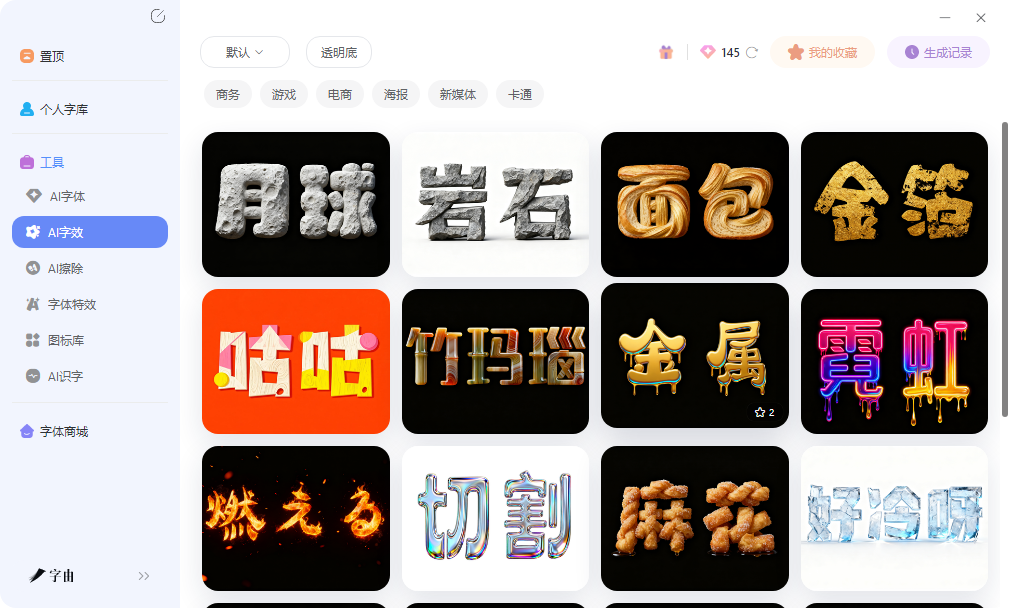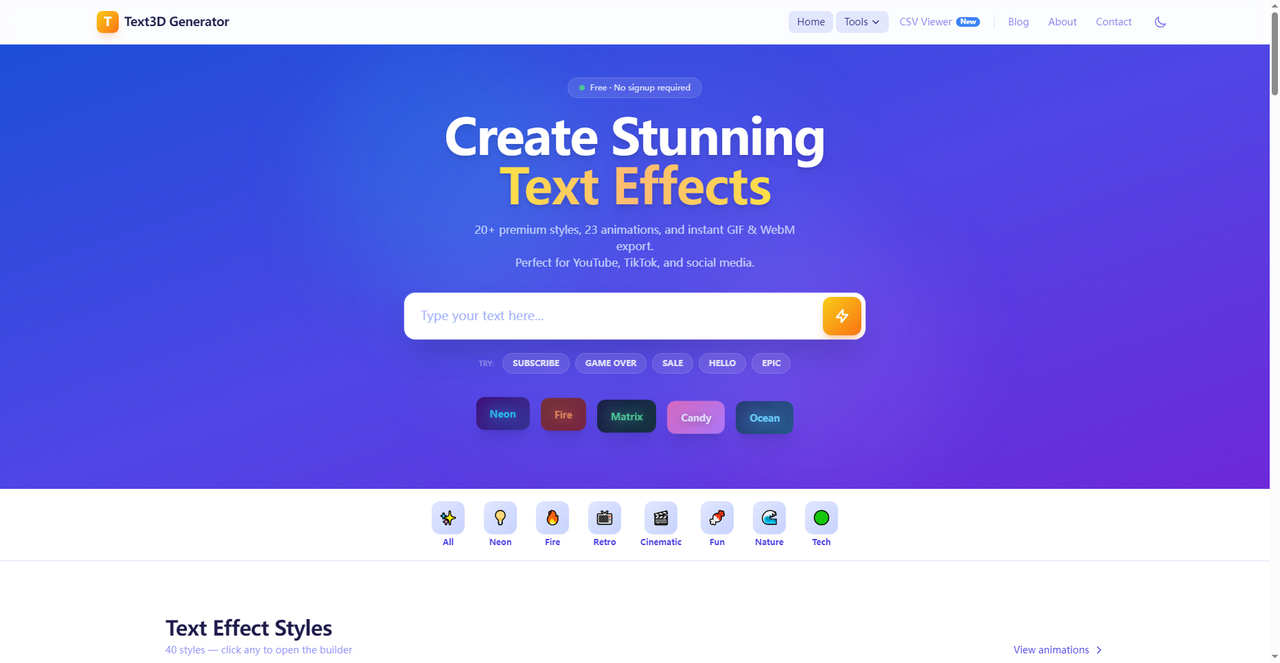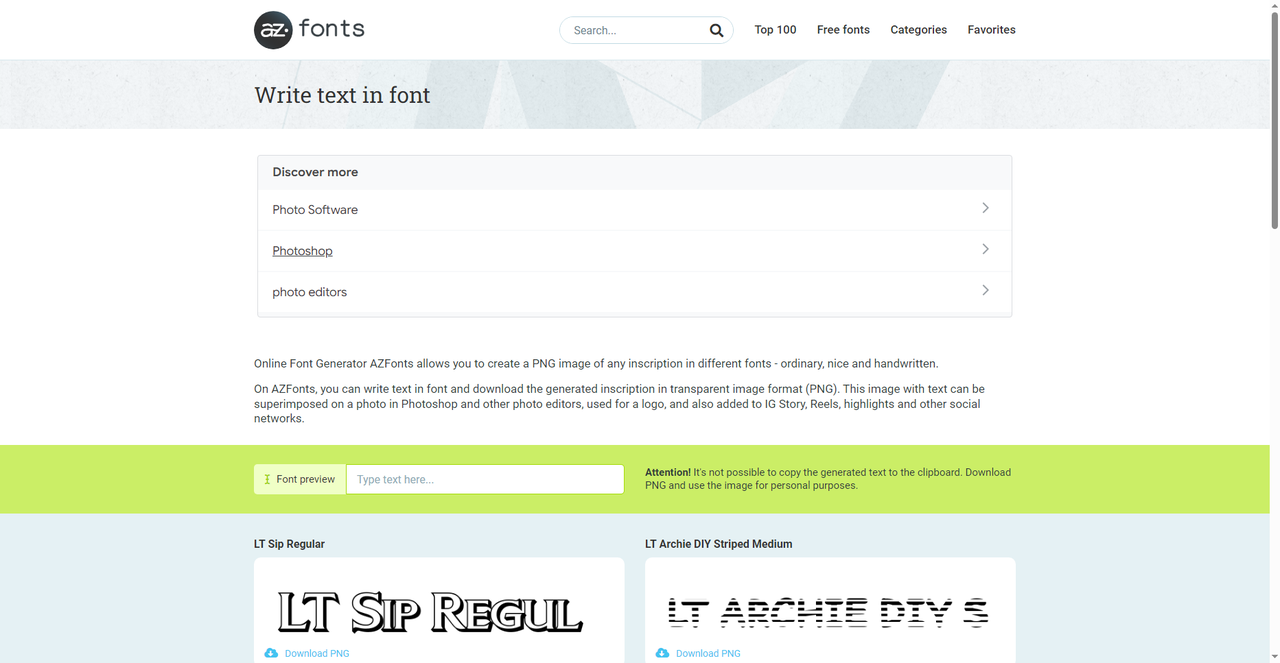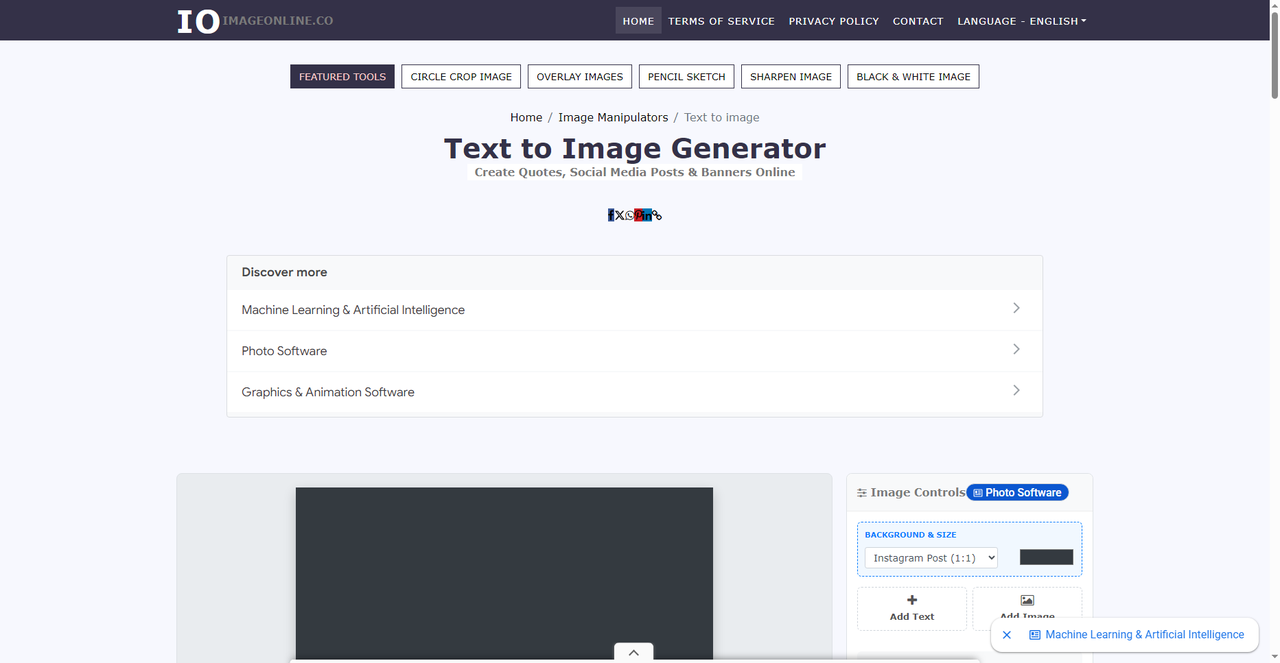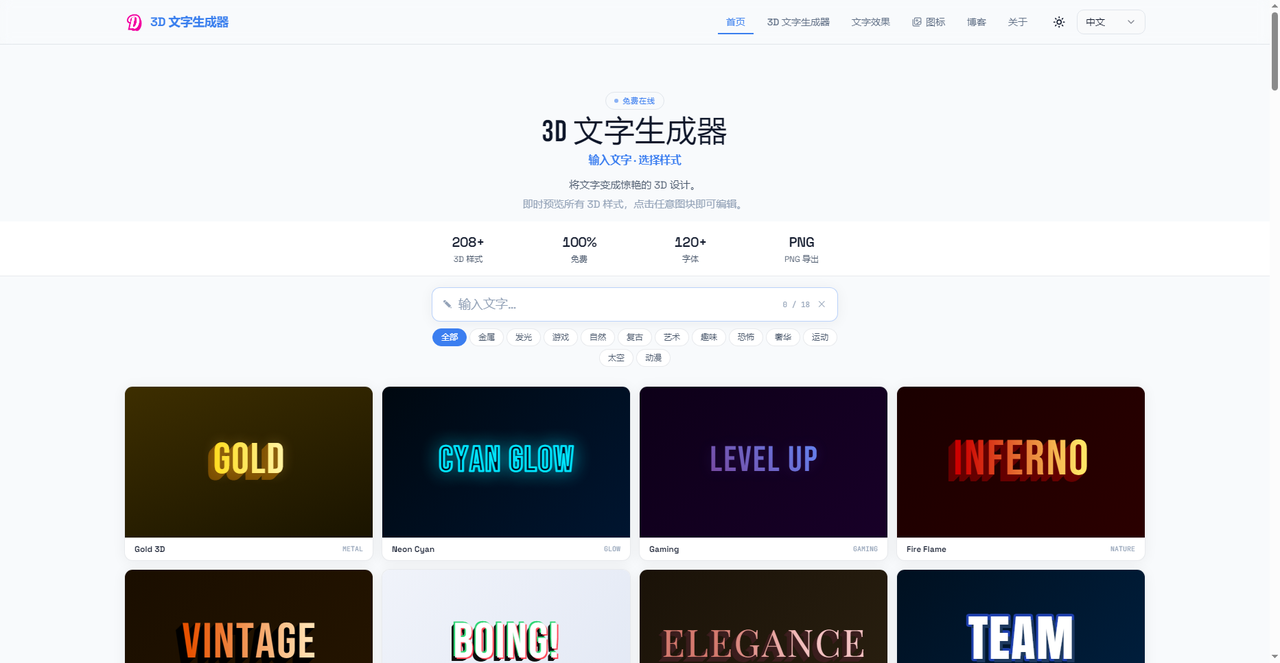
做海报标题太单调?5个免费艺术字生成器效果惊艳
做海报时标题文字总是平淡无奇,默认黑体宋体看久了毫无新鲜感。去PS里调图层样式学半天,渐变方向阴影颜色还是配不好,最后放弃用回系统字体。其实现在不少网页工具专门解决这个问题,打开浏览器输入文字就能生成带特效的艺术字图片,几分钟出一张带透明背景的PNG,直接拖进设计软件继续排版。这篇文章整理的几个生成器,有的专攻3D立体效果,有的支持自定义参数调节,有的基于正规字体库生成带授权信息的图片,还有的可以输出高分辨率精细特效,基本能满足从电商主图到社交媒体封面的各种文字特效需求。
字由不是单纯的艺术字生成器,客户端里的字体库按风格做了细分,手写体、书法体、卡通体、黑体、宋体各自归类,找起来比较直观。做海报前先在库里浏览,找到气质匹配的字体激活试用,确认效果后再用AI字效加特效,整个过程不用切换软件,省去了在字体网站下载安装、再打开PS调效果的繁琐步骤。字体激活后在设计软件里直接就能调用,不需要走系统安装流程。
AI字效支持在网页版直接操作,输入文案后选择霓虹、金属、浮雕、投影等效果类型,每种效果下还有细分变体,比如金属类就分拉丝、镜面、生锈等不同质感。调好色温、强度、光影角度后,生成带透明背景的PNG图片,可以直接拖进PS、AI、PPT里。
2、3D Text Generator
3D Text Generator是一个专门做立体文字效果的在线工具。进入网站后输入文字内容,选择3D风格模板,系统会实时渲染出带深度和透视的立体文字。可以调整文字的厚度、倒角角度、表面材质和光源方向,做出从轻微浮雕到强烈挤压的各种立体效果。生成结果支持下载PNG图片,带透明背景,直接放进海报或者PPT里就能用,不需要额外抠图。网站的操作界面比较直观,左侧是文字输入区,右侧是参数调节面板。材质选项包括金属、塑料、玻璃、木纹等常见类型,每种材质下又有细分变体,比如金属类分黄金、铬合金、生锈铁等效果。
3、AZFonts Font Generator
AZFonts的生成器基于其庞大的字体库,可以把文字转换成网站上收录的任意字体样式。输入文案后,系统会列出所有匹配的字体,每种字体都附带预览图和授权信息,商用还是个人使用一目了然。这个工具的优势在于字体来源正规,做商业项目时不用担心侵权风险,生成结果可以下载PNG图片,也可以直接复制文字样式到设计稿里。对于需要批量查看不同字体效果、快速对比选字的场景,AZFonts的效率很高。输入一段品牌标语,系统同时展示几十种字体的渲染效果,横向对比比逐个打开字体文件快得多。
4、Text to Image Generator
这个工具走自定义图片生成路线,输入文字后选择字体、颜色、背景、阴影、描边等参数,生成的是PNG图片。支持上传自定义字体文件,如果手里有一款特别的字体想做成标题图,可以直接上传使用,不需要先把字体装到系统里。输出尺寸可以调节,从几百像素到几千像素都能设置,背景也可以设置成透明或者纯色,适合做公众号封面、电商主图、PPT标题或者打印物料。
5、Text3D Generator
Text3D Generator是另一个专注立体文字效果的在线工具,和3D Text Generator相比,它的特效偏向更夸张的视觉冲击力。模板库包括金属切割、霓虹发光、火焰燃烧、冰晶雕刻、激光射线等风格,选择模板后输入文字,可以调整主色、辅色、光影角度、表面材质、文字间距、背景透明度等参数,生成高分辨率的PNG或GIF。网站支持中文输入,部分模板对中文字符的渲染效果不错,笔画细节和间距处理比较到位,做中文海报时不会出现笔画粘连或者间距失衡的情况。
网页工具打开就能操作,3D Text Generator和Text3D Generator的立体特效对做海报和封面比较友好,导出图片直接可用;AZFonts在字体授权方面比较规范,做商业项目查起来省心;Text to Image Generator对想自定义参数的人更友好。字由